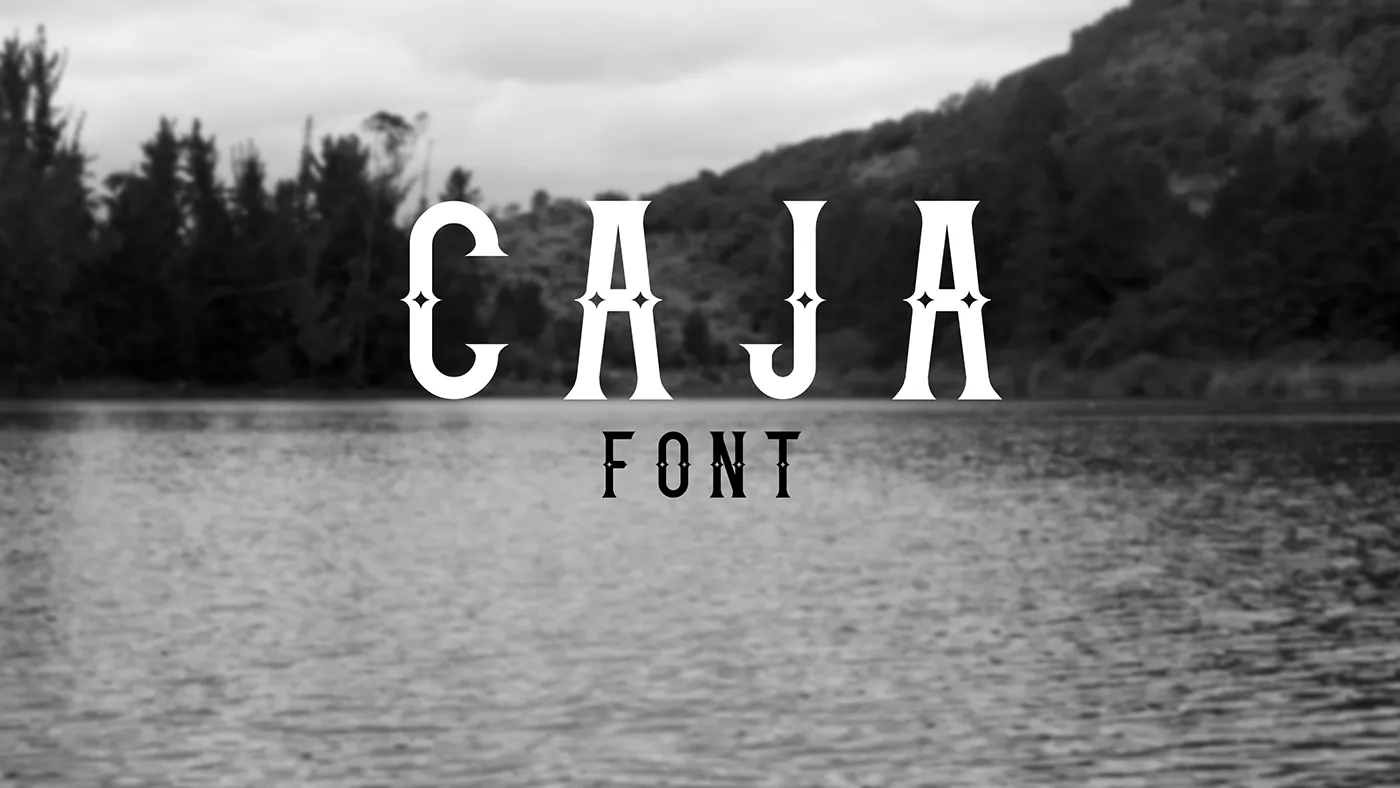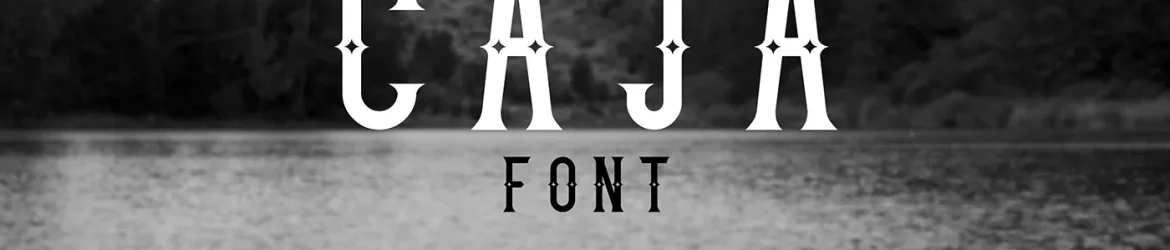
Caja Font é uma fonte totalmente em maiúsculas que apresenta um sabor vintage e elegante, ideal para estilos góticos. Esta criativa escolha do designer geovanny Gavilanes, um jovem talentoso de Quito, na Espanha do Sul, oferece aos designers a oportunidade de dar uma captação única às suas criações digitais. Como fonte livre e totalmente em maiúsculas, Caja Font é particularmente versátil para aplicações como headlines ou branding, adicionando um toque distinto ao seu trabalho. Se você busca uma fonte que não apenas oferece uma aparência clara e agradável, mas também transmite elegância e estilo vintage através de suas linhas modernas, Caja Font é definitivamente uma opção a ser considerada.